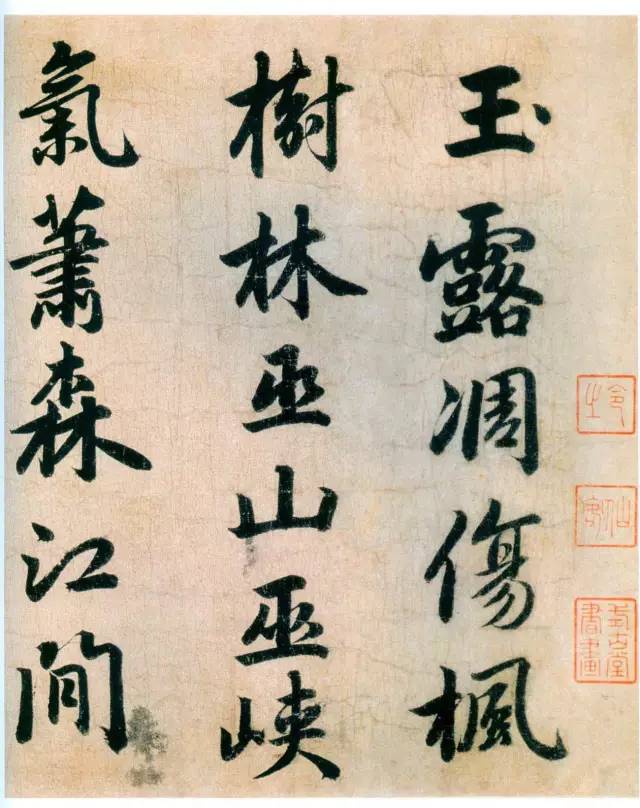
字体全名: 汉标赵孟頫杜甫秋兴诗四首
字体简介: 下载须知:本字库非标准GB2312字库。本字库只包含了赵孟頫《杜甫八首》真迹上的“317个字”。详见图样。赵孟頫《杜甫八首》(沈君求书,因纸短仅书其中四首),上海博物馆藏。 此卷书于元初至元十九年(1282)前后,作者时年28岁左右,此书用笔细腻,结体端庄秀逸,笔圆墨润,筋丰骨健,给人以神定气闲,虚和宛朗的美感。